안병국의 웹타이포그래피 – 헤드카피와 서브카피의 관계.2
MAIN 카피와 SUB카피의 폰트값 설정
상황에 따라 글자의 폭과 길이, 행간등을 다양하게 적용하여 사용하겠지만 보편적인 경우 메시지의 강한 전달력을 위해 메시지가 퍼지는 느낌보다는 견고한 느낌을 선호하게 된다. 견고함을 주기 위한 방편으로 자간, 장평등을 기본값을 본래의 기본값보다 작은 수치 값을 선호하게 되는데 장평은 보통 90~95% 정도를 많이 사용하며, 자간은 -10에서 -50값을 주로 많이 사용하고 있다. 장평 값을 많이 주게 되면 글자를 보는 안정된 구도가 훼손되어 심미성이 떨어지게 되고 자간 값을 많이 주면 글자간의 폭이 넓어져 견고한 느낌이 사라지게 되기 때문이다.
또한 MAIN 카피는 사이트의 성격과 디자인 콘셉트에 따라 다양한 서체가 사용될 수 있는데 SUB카피는 앞에서 언급했듯 안정감과 견고함을 주기 위해 고딕계열의 서체가 주로 많이 사용되며, 특히 고딕 계열 중에서도 Medium과 BOLD체를 선호하는 경향이 있다. 그렇기 때문에 SUB카피로 많이 사용되는 한글 폰트는 윤고딕 500계열과 윤고딕 150계열, 산돌고딕이 주를 이룬다.
고딕 계열 중에서도 다양한 변형 폰트들이 있긴 하나 SUB 카피가 조그마한 크기로 사용되기 때문에 변형 폰트 보다는 고딕 본래의 모양에 충실한 폰트를 사용함으로써 안정감과 견고함을 주기 위함이며, 또한 MAIN 카피로 명조나 손글씨, 장식체가 사용된 경우, 이를 보완하기 위한 방편으로 많이 사용되고 있다.
명조체를 SUB 카피에 이용하는 경우도 종종 있는데 이런 경우는 고딕체를 사용할 때보다 글자의 크기를 늘려 안정감을 꾀하면서 사용한다. 명조는 같은 크기라 하더라도 고딕에 비해 글자가 작게 되면 가독성이 현저히 떨어질 수 있기 때문이다.
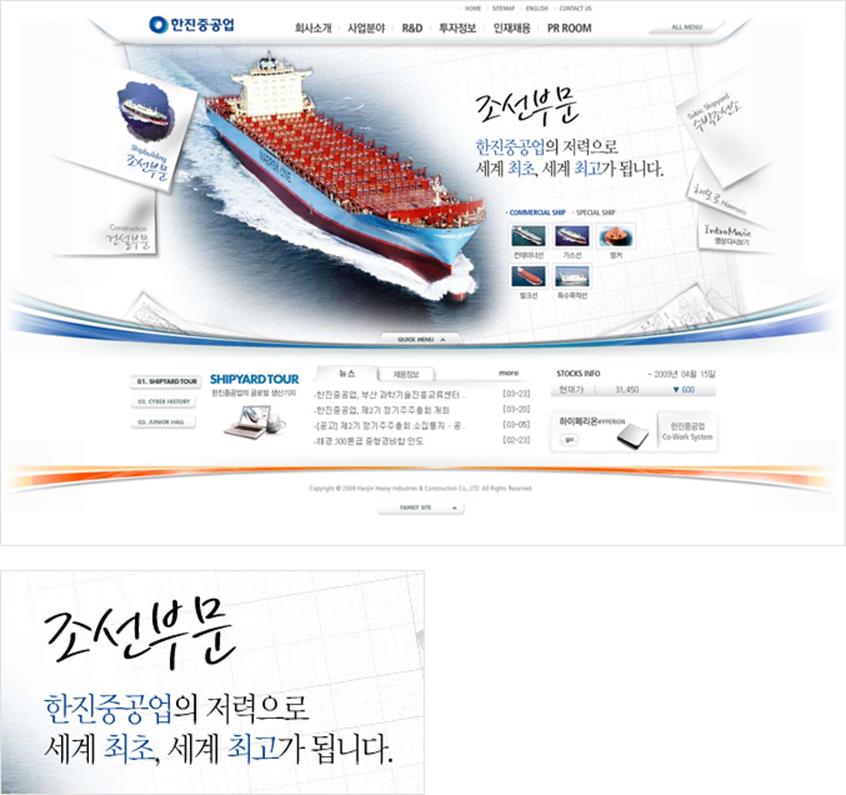
MAIN 카피와 SUB카피간의 위치 설정
SUB 카피의 위치는 MAIN 카피에 의해 많이 좌우 되는데 특히 서체 모양에 따라 MAIN카피의 위에 위치 시킬지 아래에 위치 시킬지 결정되게 된다. MAIN 카피가 명조나 봄날체 같은 손글씨 또는 장식체로 되어 있는 경우 폰트가 얇고 고딕에 비해 틈이 많이 생기기 때문에 고딕계열의 SUB카피를 밑에 위치시킴으로 안정감을 꾀하고 고딕계열로 되어 있는 경우에는 명조 계열에 비해 글자만으로도 무게감이 실리기 때문에 위 아래에 상관 없이 화면 전체의 레이아웃을 고려해 위치시키게 된다.
그러나 영문의 경우 고딕체라 하더라도 대문자와 소문자가 혼합되어 있을 때는 특성상 글자 상단부분에 변형이 많이 가해지기 때문에 SUB 카피를 하단에 위치 시키는 것이 안정적이라 할 수 있다.
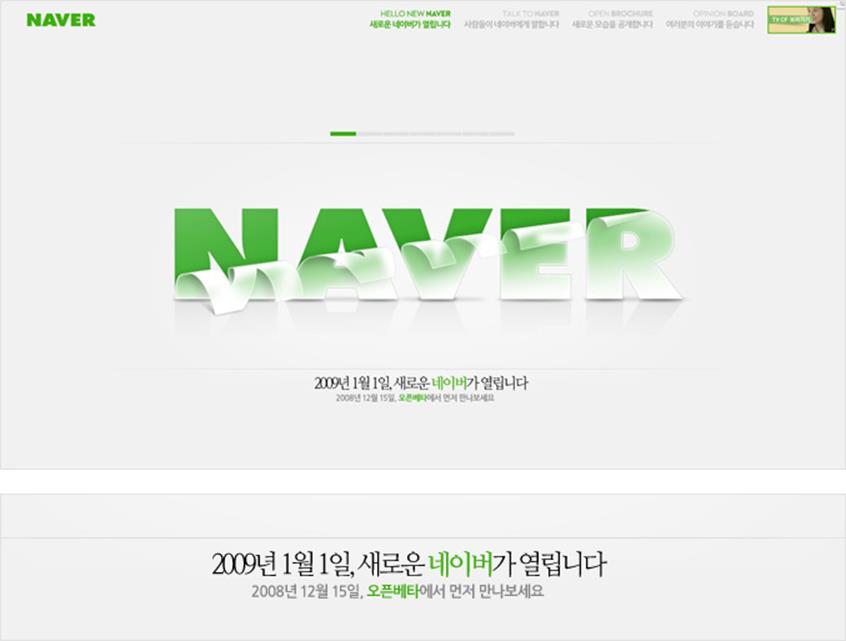
▲ MAIN 카피가 명조체로 되어 있는 경우의 일반적 위치 관계
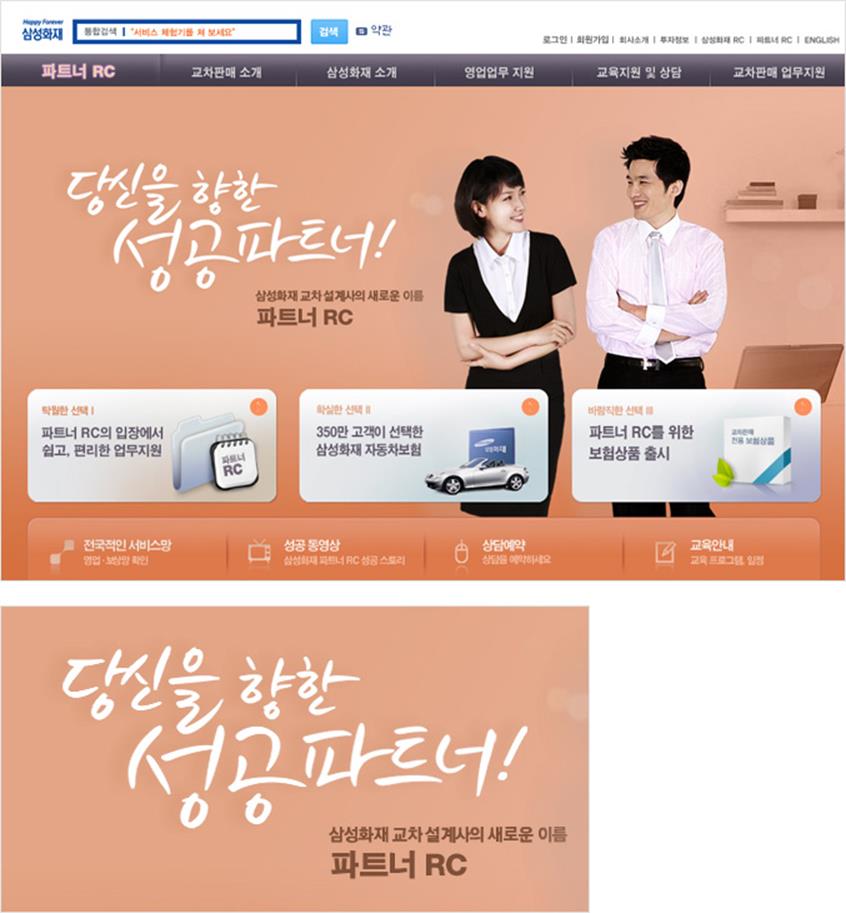
▲ MAIN 카피가 손글씨로 되어 있는 경우의 일반적 위치 관계
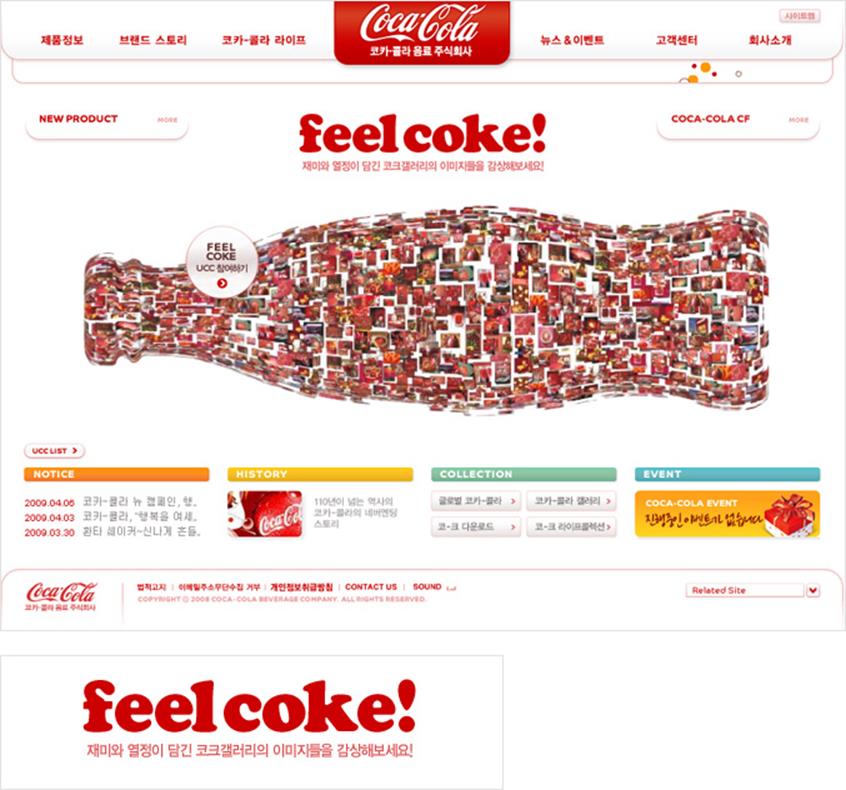
▲ MAIN 카피가 장식체로 되어 있는 경우